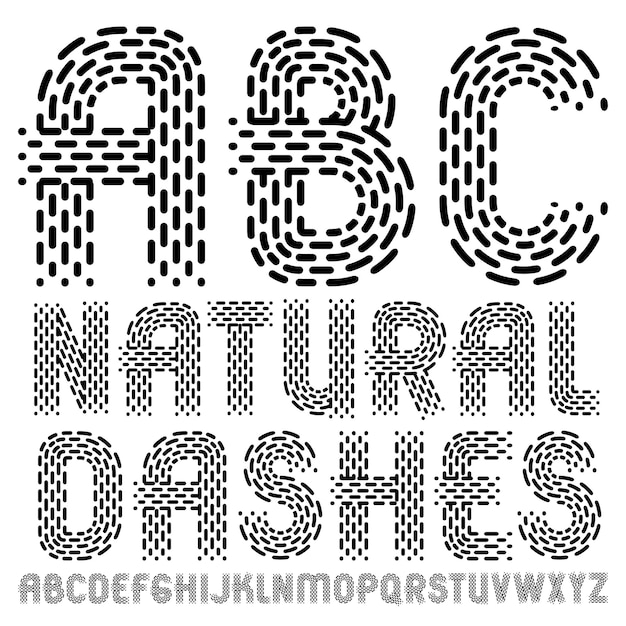
Векторные фанки сжатые заглавные буквы английского алфавита, коллекция abc. Округлый полужирный шрифт, шрифт от а до я может использоваться в дизайне ретро-плаката. Создано с помощью штрихов, параллельных линий.Векторные фанки сжатые заглавные буквы английского алфавита, коллекция abc. Округлый полужирный шрифт, шрифт от а до я может использоваться в дизайне ретро-плаката. Создано с помощью штрихов, параллельных линий.
Векторные фанки сжатые заглавные буквы английского алфавита, коллекция abc. Округлый полужирный шрифт, шрифт от а до я может использоваться в дизайне ретро-плаката. Создано с помощью штрихов, параллельных линий.